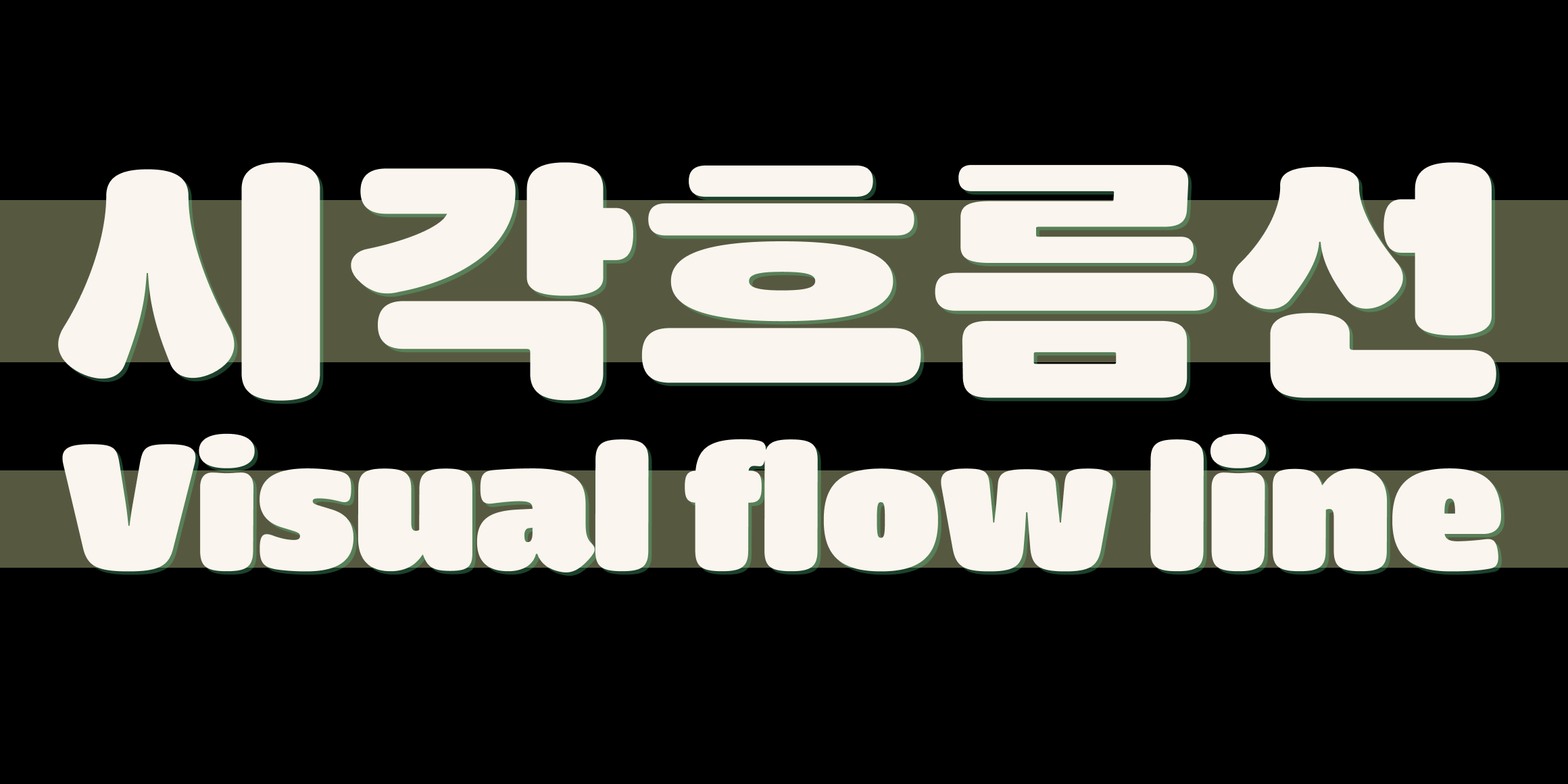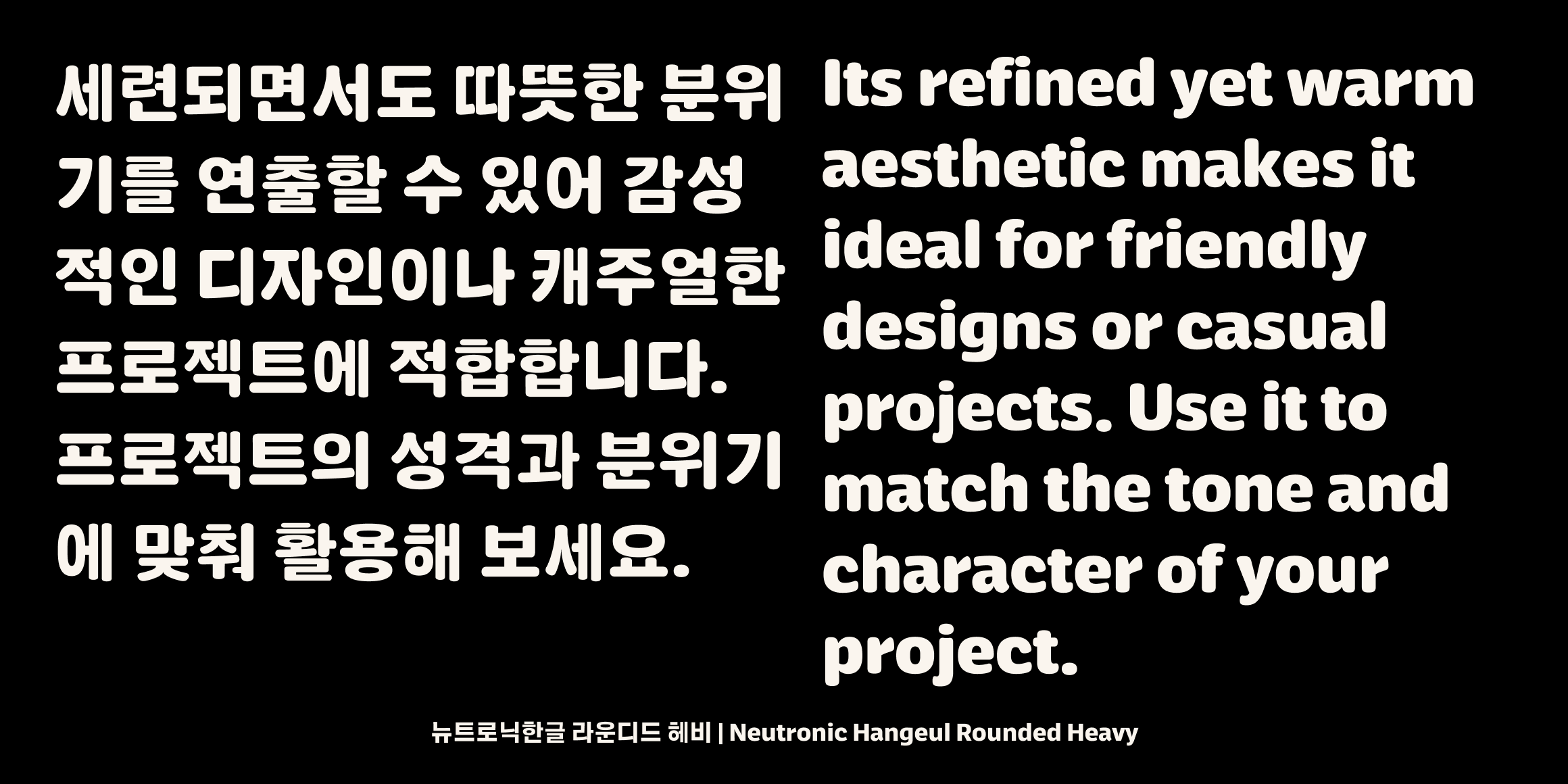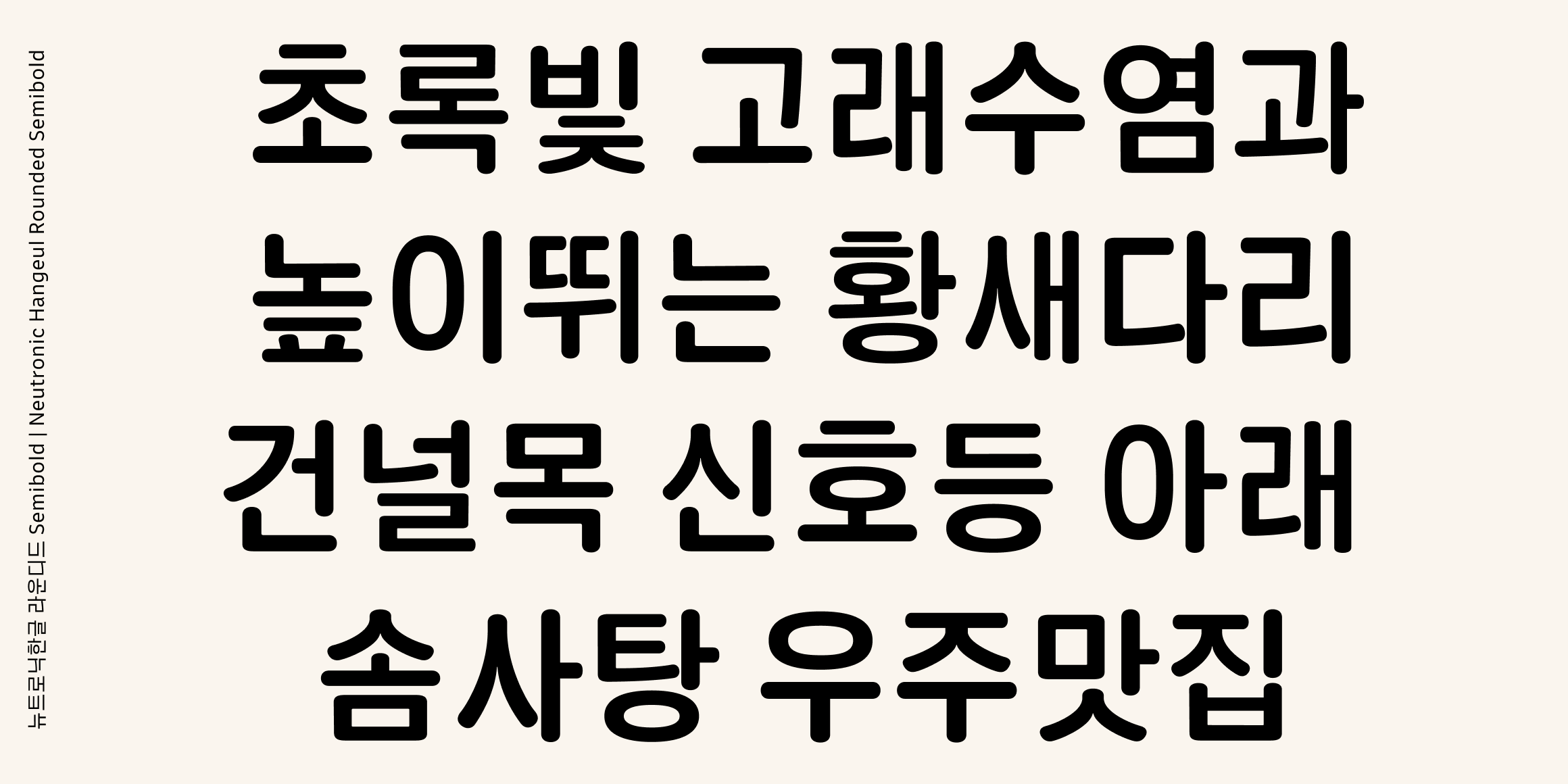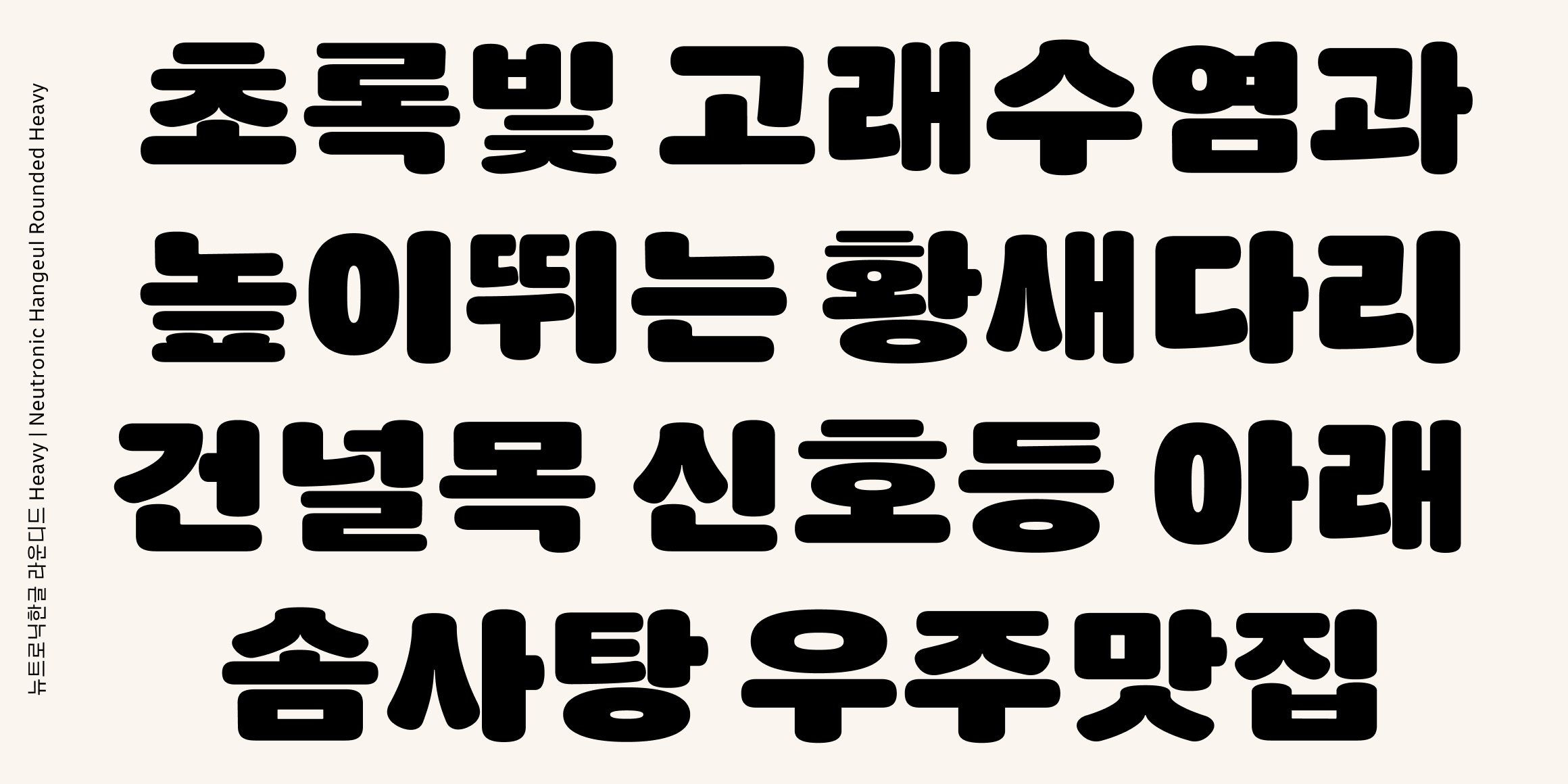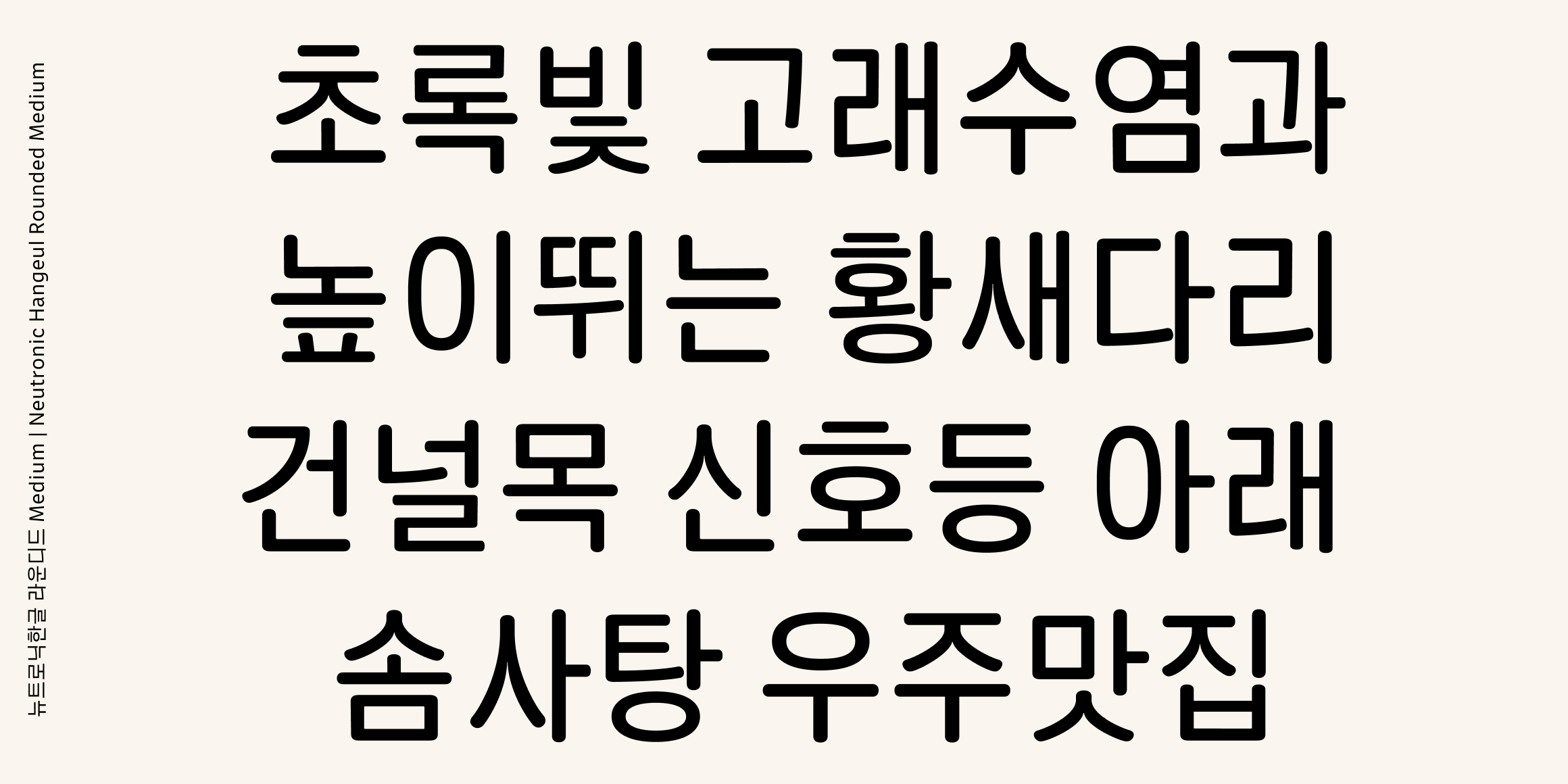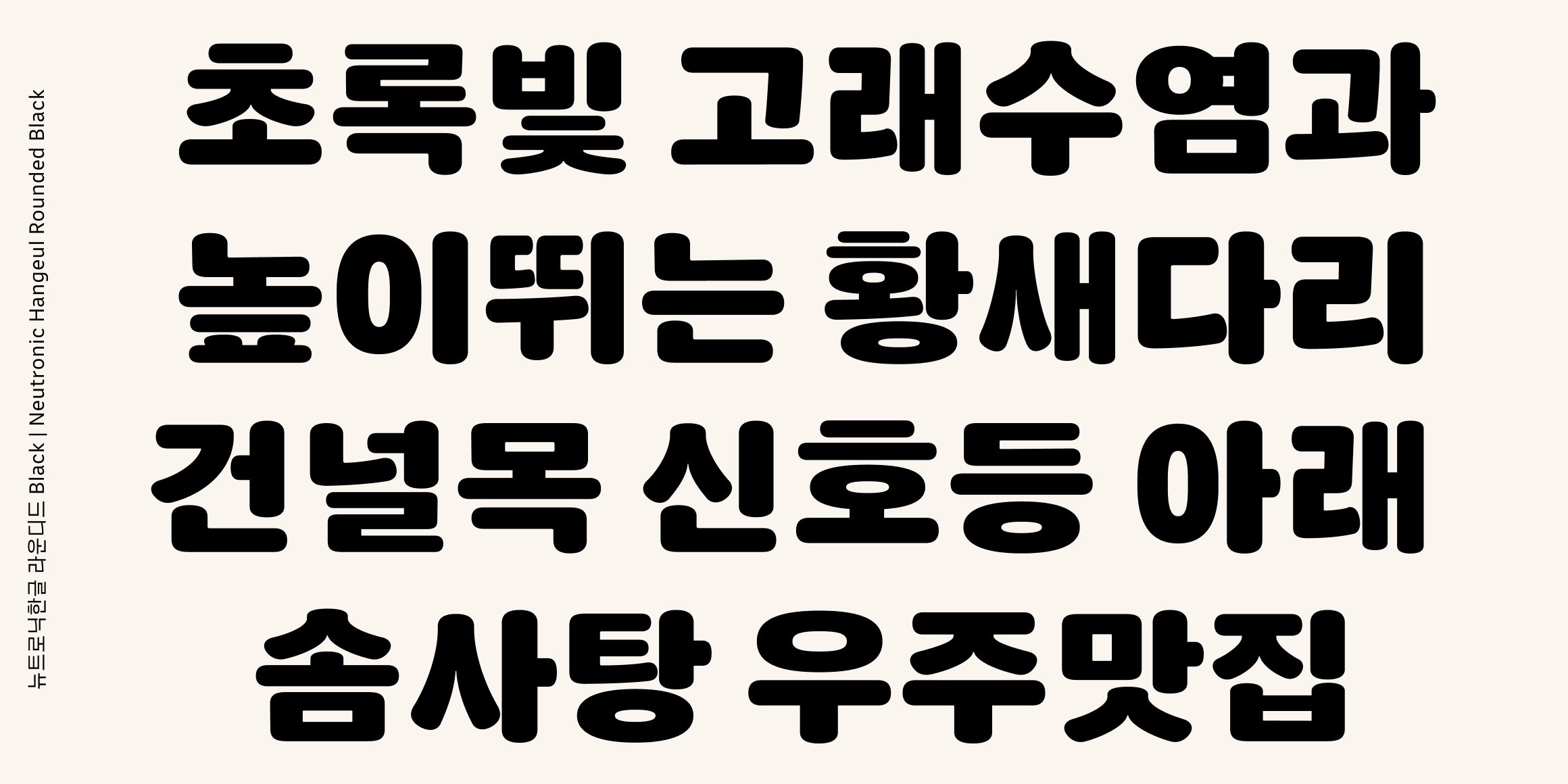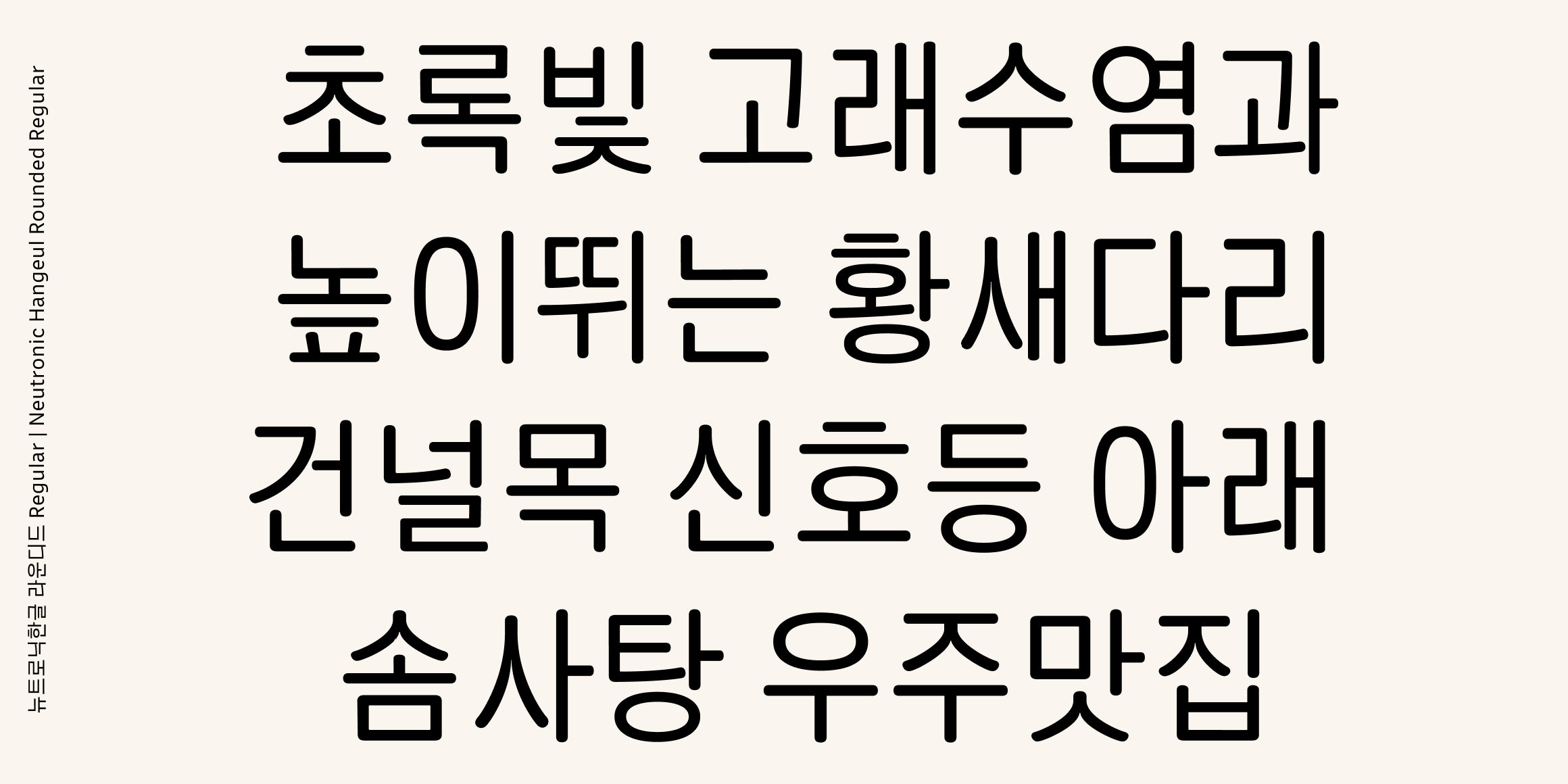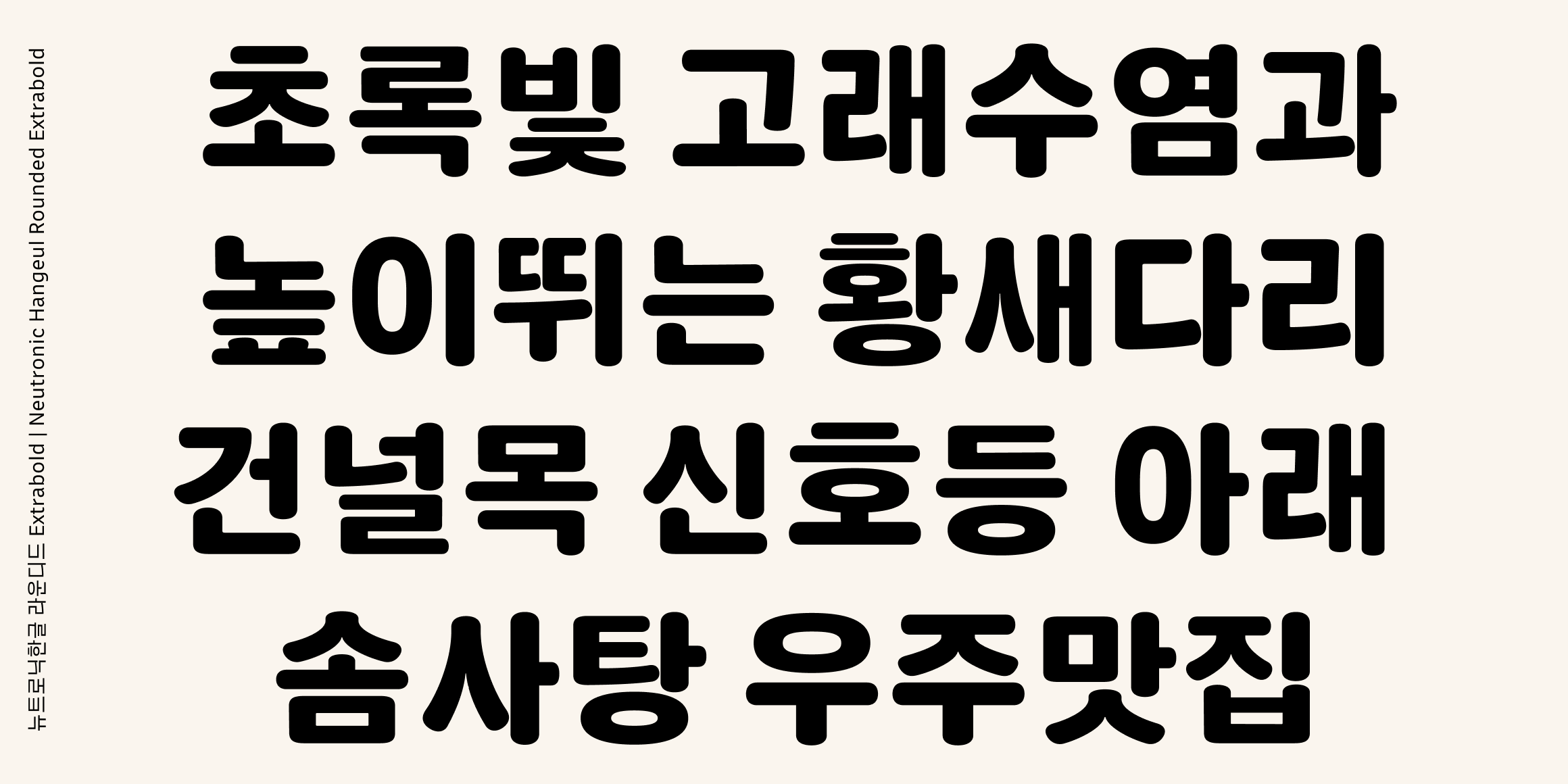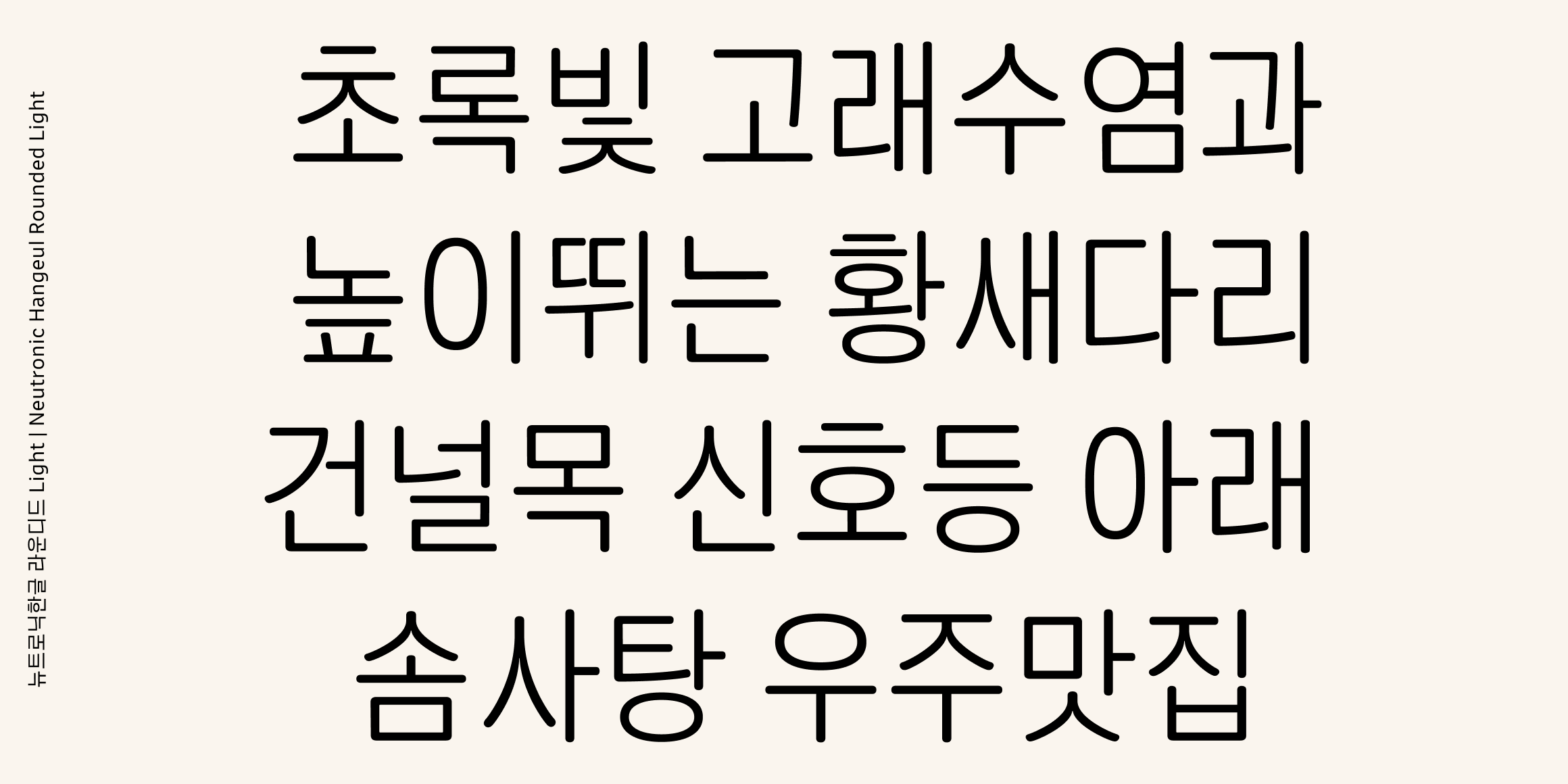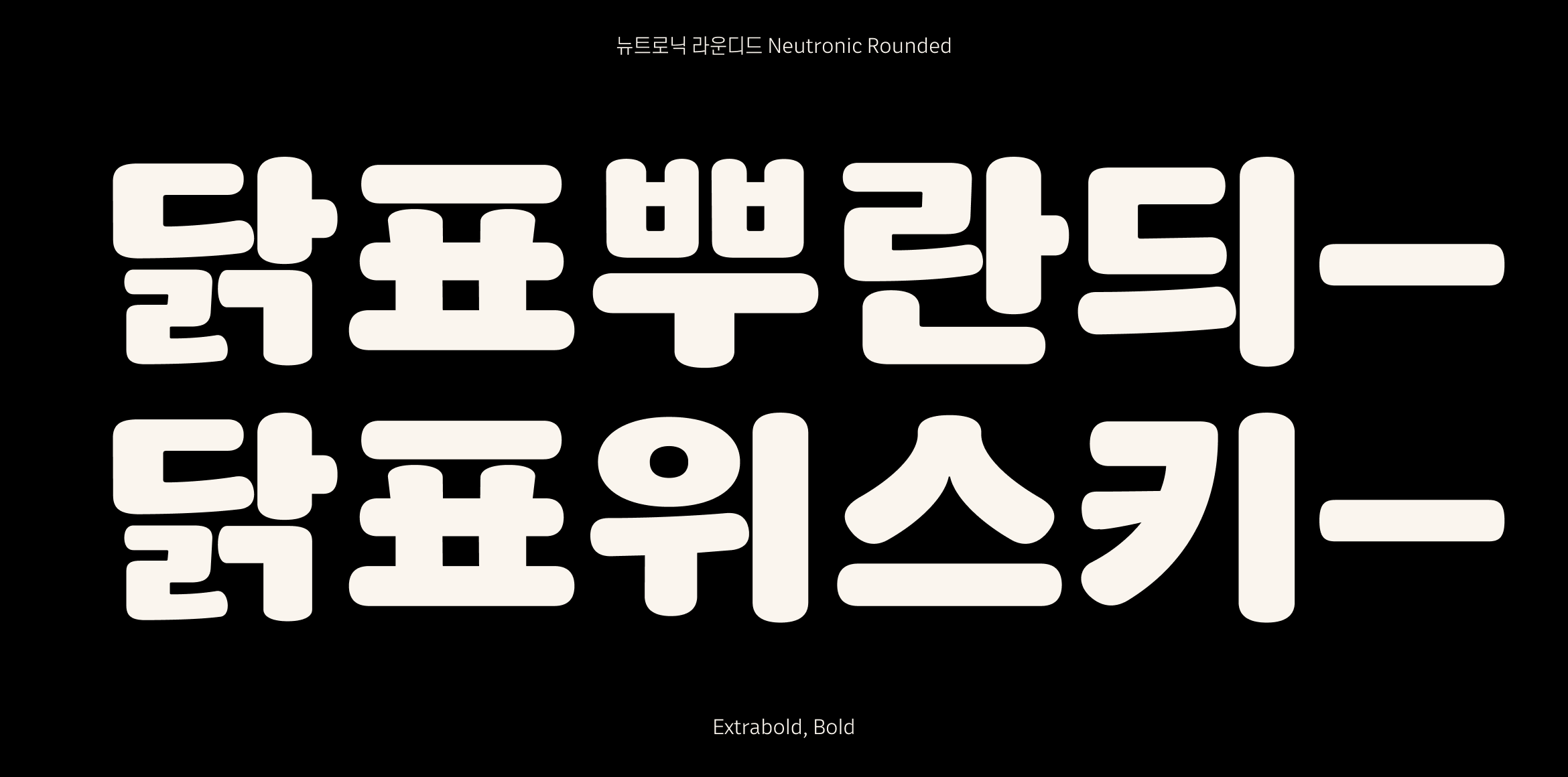
Neutronic Hangeul Rounded
Hypertype
뉴트로닉한글 라운디드는 획의 끝부분을 부드러운 곡선으로 처리하여 온화하고 친근한 인상을 줍니다. 세련되면서도 따뜻한 분위기를 연출할 수 있어 감성적인 디자인이나 캐주얼한 프로젝트에 적합합니다. 프로젝트의 성격과 분위기에 맞춰 활용해 보세요.
• 뉴트로닉한글 라운디드 / Neutronic Hangeul Rounded